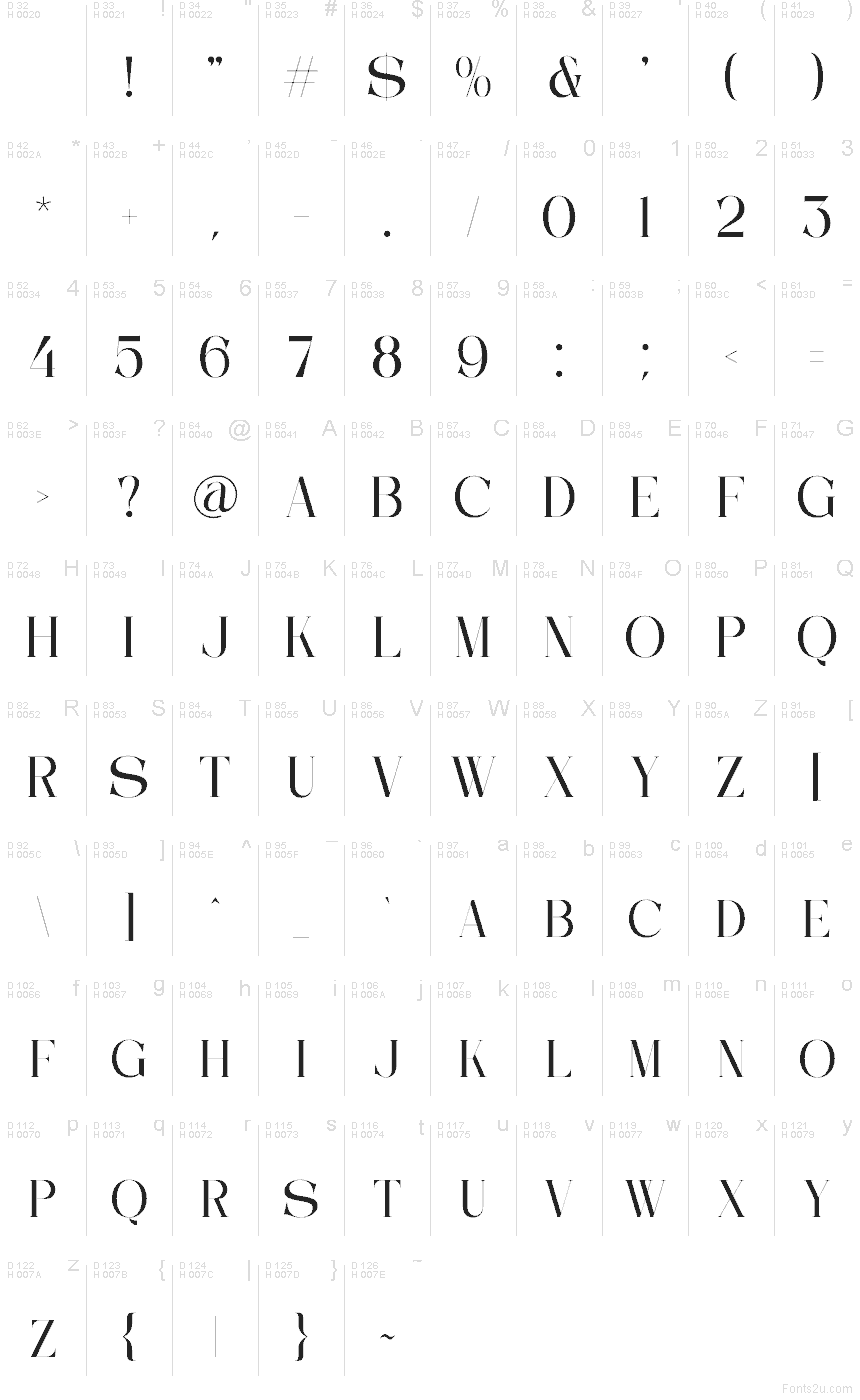
Moonlit Charm od TimelessType je bezplatné patkové písmo s vysokým kontrastem a moderní náladou Didone. Písmena působí vyváženě a snově, jako z obálek starých časopisů. Kombinují vlasové detaily s vysokými, elegantními tvary a širokými křivkami, díky čemuž si písmo zachovává vytříbený vzhled bez zbytečných příkras.
Hodí se pro módní branding, kosmetické obaly, redakční titulky, pozvánky a filmové názvy, kde potřebujete bezplatný font, který působí profesionálně a přitom dramaticky. Použijte jej, když potřebujete, aby několik slov mělo skutečnou váhu – silný kontrast a elegantní verzálky dodají krátkým titulkům, monogramům a textům na obálkách formální, téměř filmový nádech.